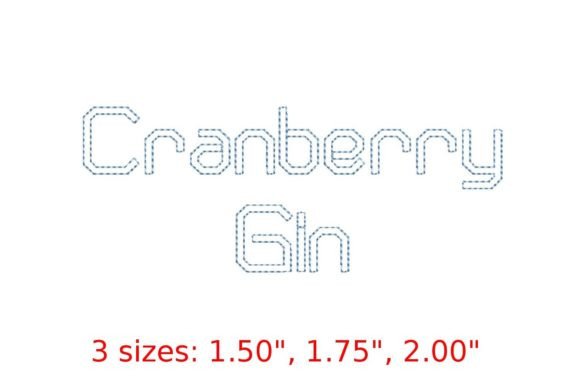
Cranberry Gin Bean Stitch Outline Font
Mencari elemen reka bentuk yang sesuai boleh menjadi mencabar, tetapi Cranberry Gin Bean Stitch Outline Font menawarkan koleksi luar biasa yang menaik taraf karya anda serta-merta.